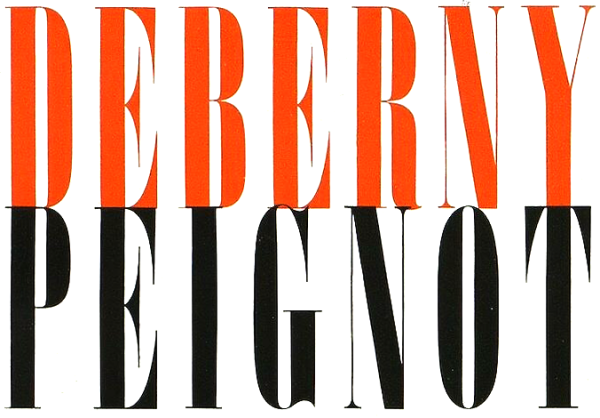
Deberny & Peignot
• Land: Frankreich
• Gegründet: 1923
• Status: nicht mehr aktiv
Die Fonderie Deberny et Peignot entstand 1923 durch den Zusammenschluss der Schriftgießereigen Peignot und Laurent & Deberny.
Ein Meilenstein der Firmengeschichte war die 1957 veröffentliche Univers-Familie von Adrian Frutiger. Sie erschien simultan für Handsatz, Monotype-Maschinensatz und im damals neuen Fotosatz. Die Großfamilie mit ihrem neuen Nummerierungssystem setzte zu dieser Zeit völlig neue Maßstäbe im Bereich der Schriftfamilienentwicklung.
Das Unternehmen wurde 1972 von der Haas Type Foundry übernommen.